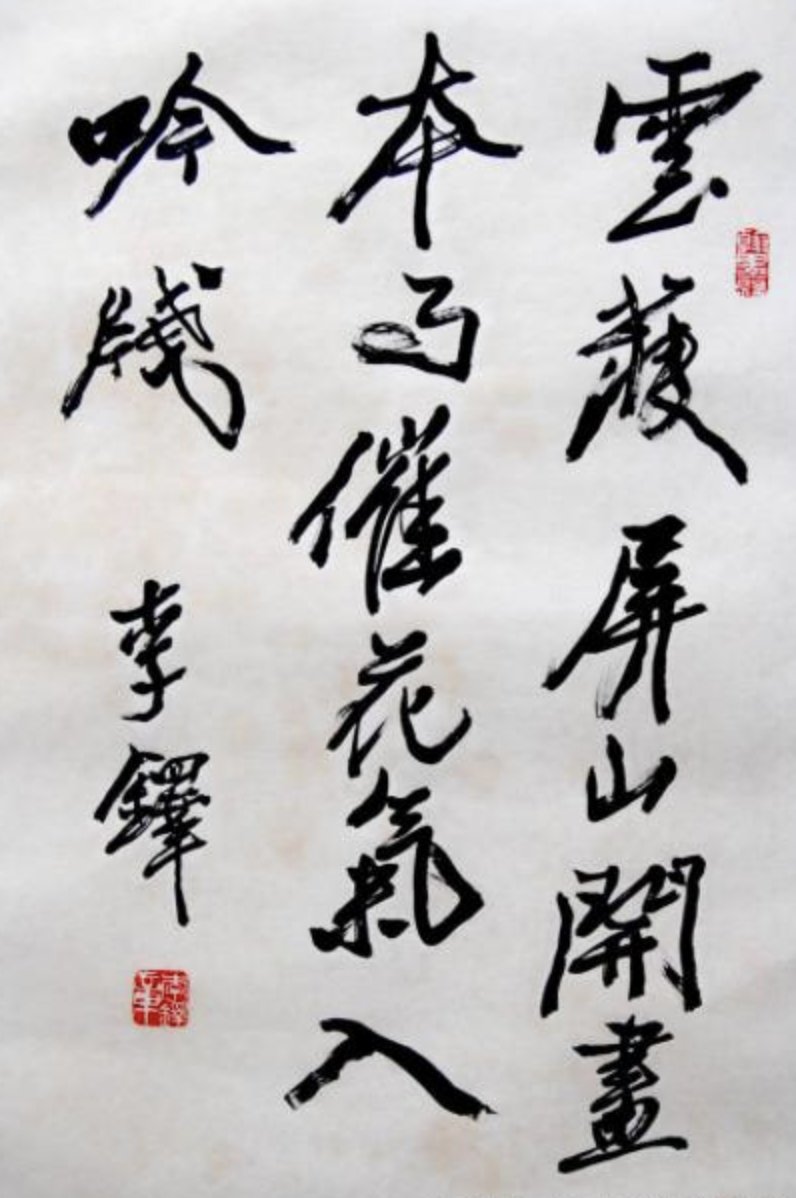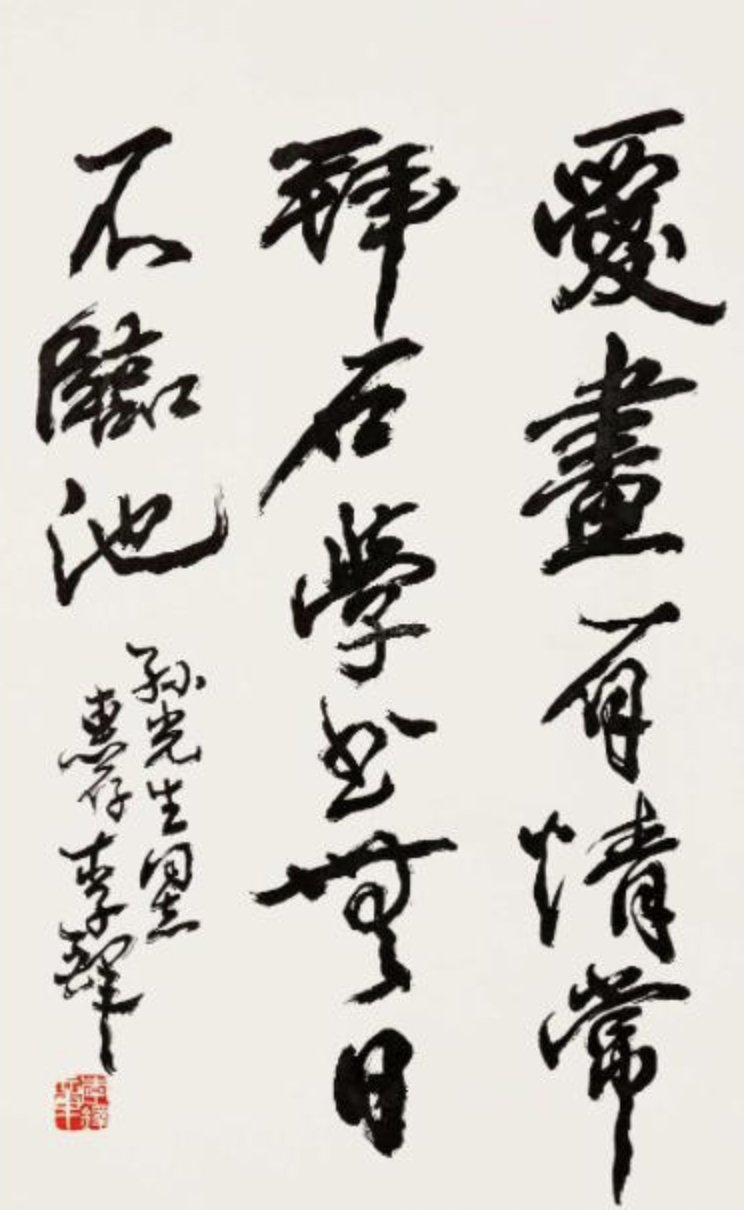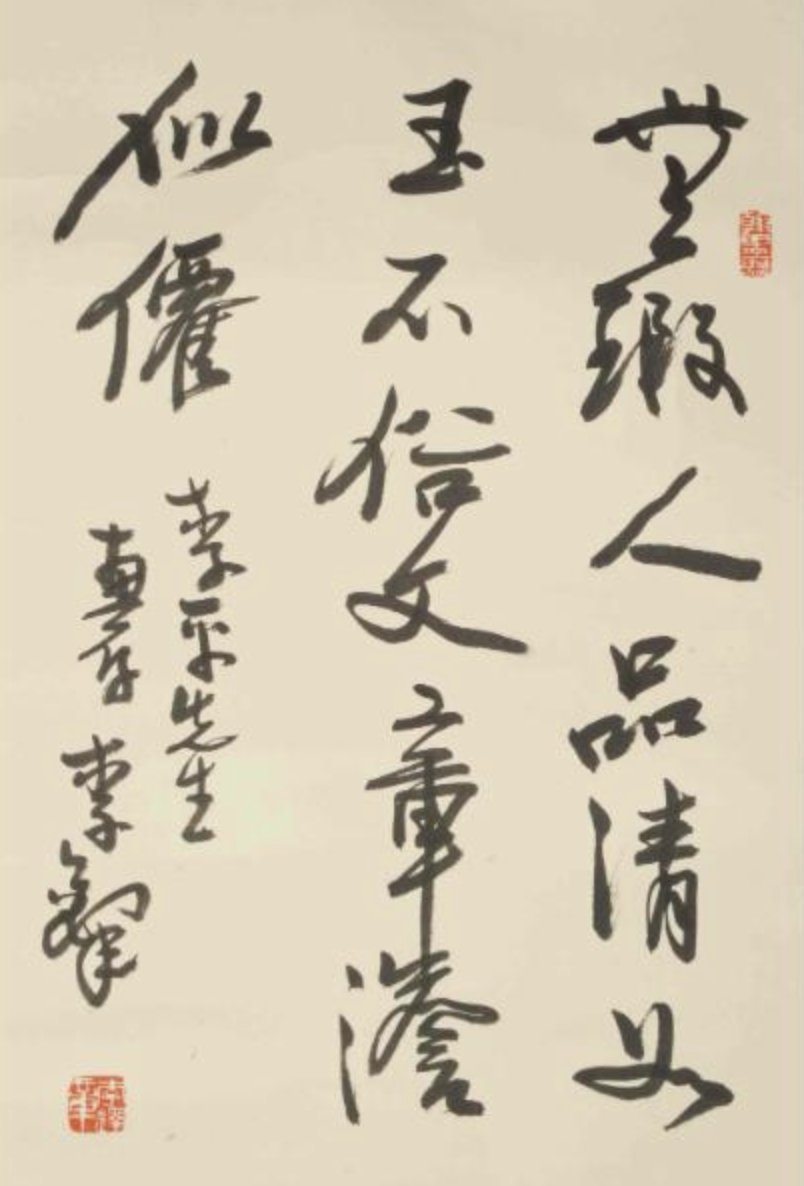
李铎书法作品欣赏
李铎,1930年生于湖南省醴陵市。中国著名书法家、军人。
历任中国人民革命军事博物馆研究员、
第九届全国政协委员、第六届全国文联委员、第三届中国书法家协会副主席、第四届中国书协顾问、
中国国际友好联络会理事、中国书画函授大学特约教授、中国国际书画艺术研究会顾问,中国文学艺术界联合会第十届荣誉委员, 享受政府特殊津贴。
李铎的书法势大力沉,取法高古,不拘一格,笔锋坚韧,让人心生敬佩!
业内公认李铎的书法可比清代大书法家王铎,李铎也曾在春晚舞台展示过自己的书法字体!